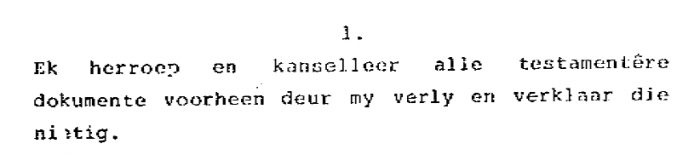
Schriftart und Alter
Das Testament im Anhang soll 1985 erstellt worden sein.
Frage 1: Welche Schriftart ist es?
Frage 2: Wann wurde diese Schriftart entwickelt?
Für mich sieht es eher nach Schreibmaschine aus. Was lässt Dich denn vermuten, dass das eine Fälschung sei? Und willst Du tatsächlich ein Testament weltöffentlich publizieren, dass ggf. Gegenstand eines Rechtstreites ist? Hast Du das Original (oder eine beglaubigte Kopie)?
Ja das ist ist gut möglich. Ich wusste nicht, dass Schreibmaschinen schon Blocksatz schreiben konnten.
Zumind. 2 Zeilen des ersteingestellten PDF haben einen über die ganze bzw. fast die ganze Blattbreite reichenden weißen Streifen, was eher für Tintenstrahldrucker spräche, bei der eine Düse mal nicht so recht wollte, oder eine Nadel beim Nadeldrucker ...
... wenn es nicht ein Scanfehler an einer Papierfalte war ...
Unter elektronischen Schreibmaschinen, die erst die ganze Zeile speichern und dann in einem Rutsch auf's Papier bringen, sollten sich auch welche finden lassen, die bei der Gelegenheit Blocksatz machen können ...
Apropos Scan ... Das ganze sieht eher nach Fax aus ...? Also fehlt vermutlich das Original?
Ansonsten täte ich stark auf eine Courier als Schriftart tippen und die gibt es gefühlt schon ewig, auf jeden Fall schon weit vor 1985 für Rechner wie für Schreibmaschinen. Von daher dürfte die Schriftart nix zur Lösung der Hauptfrage beitragen können ... Da müsste man schon am Original ganz tief in die Details einsteigen, ob man evtl. Indizien für eine Version nach 1985 zu finden. Beim Blick in die drei Schriftmuster in der Wikipedia erkenne ich nur, dass es wohl nicht die Adobe-Version ist, die weicht leicht ab bspw. in B und H (Höhe mittlerer waagerechter Strich).
Interessanter könnten da die beiden Stempel sein ... Weil die nutzen ab und werden dann evtl. in einer anderen Schriftart nachproduziert? Da ist dann aber Wissen über die Stempelgenerationen gefragt, die hier eher keiner haben wird ...
Ja, natürlich gab's die.